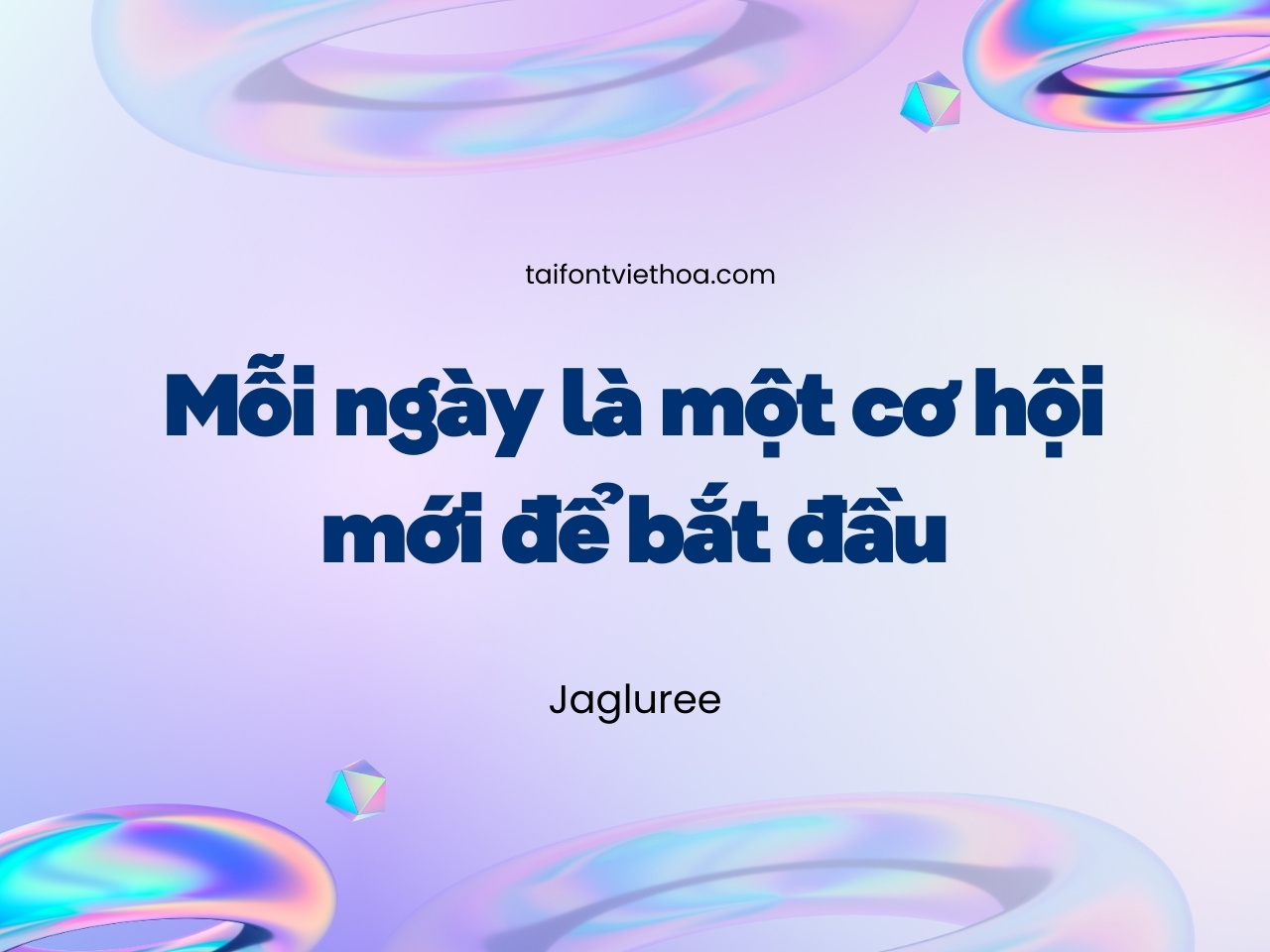
Font việt hóa Và Mod Jagluree+
Tác giả Font: Maulana Creative
Giới thiệu về font Và Mod Jagluree+
Và Mod Jagluree+ là một font chữ độc đáo kết hợp giữa phong cách hiện đại và nghệ thuật typography cổ điển. Font mang hơi hướng thời trang với các chi tiết cách điệu tinh tế, phù hợp để tạo điểm nhấn trong các thiết kế sang trọng hoặc sáng tạo. Phiên bản Việt hóa được thực hiện bởi Catterio, hỗ trợ đầy đủ tiếng Việt với hệ dấu thiết kế chỉn chu, rõ ràng. Ngoài tiếng Việt, font còn hỗ trợ hơn 50 ngôn ngữ khác nhờ tích hợp bảng mã Latin và Latin Extended. Font này đã được taifontviethoa.com chọn lọc, kiểm thử thực tế trong nhiều dự án thiết kế in ấn và kỹ thuật số, phục vụ cộng đồng sáng tạo trong nước.
Đặc điểm thiết kế và ứng dụng của Và Mod Jagluree+
Font sở hữu nét chữ cân đối, có độ đậm rõ ràng và nhiều chi tiết uốn lượn tạo nên sự mềm mại nhưng vẫn giữ được sự sắc sảo. Các ký tự hoa được cách điệu giúp tăng hiệu ứng thị giác, rất lý tưởng cho các thiết kế cần tính thẩm mỹ cao. Phong cách của font này vừa cổ điển, vừa hiện đại, dễ dàng kết hợp với các bố cục thiết kế sáng tạo.
Font phù hợp với các dự án thiết kế logo, bao bì mỹ phẩm, bìa sách nghệ thuật, tiêu đề tạp chí, sản phẩm thời trang hoặc bộ nhận diện thương hiệu cao cấp. Các ngành nghề lý tưởng gồm: thời trang, mỹ phẩm, nghệ thuật, sáng tạo nội dung, thương hiệu cao cấp và quảng cáo truyền thông.